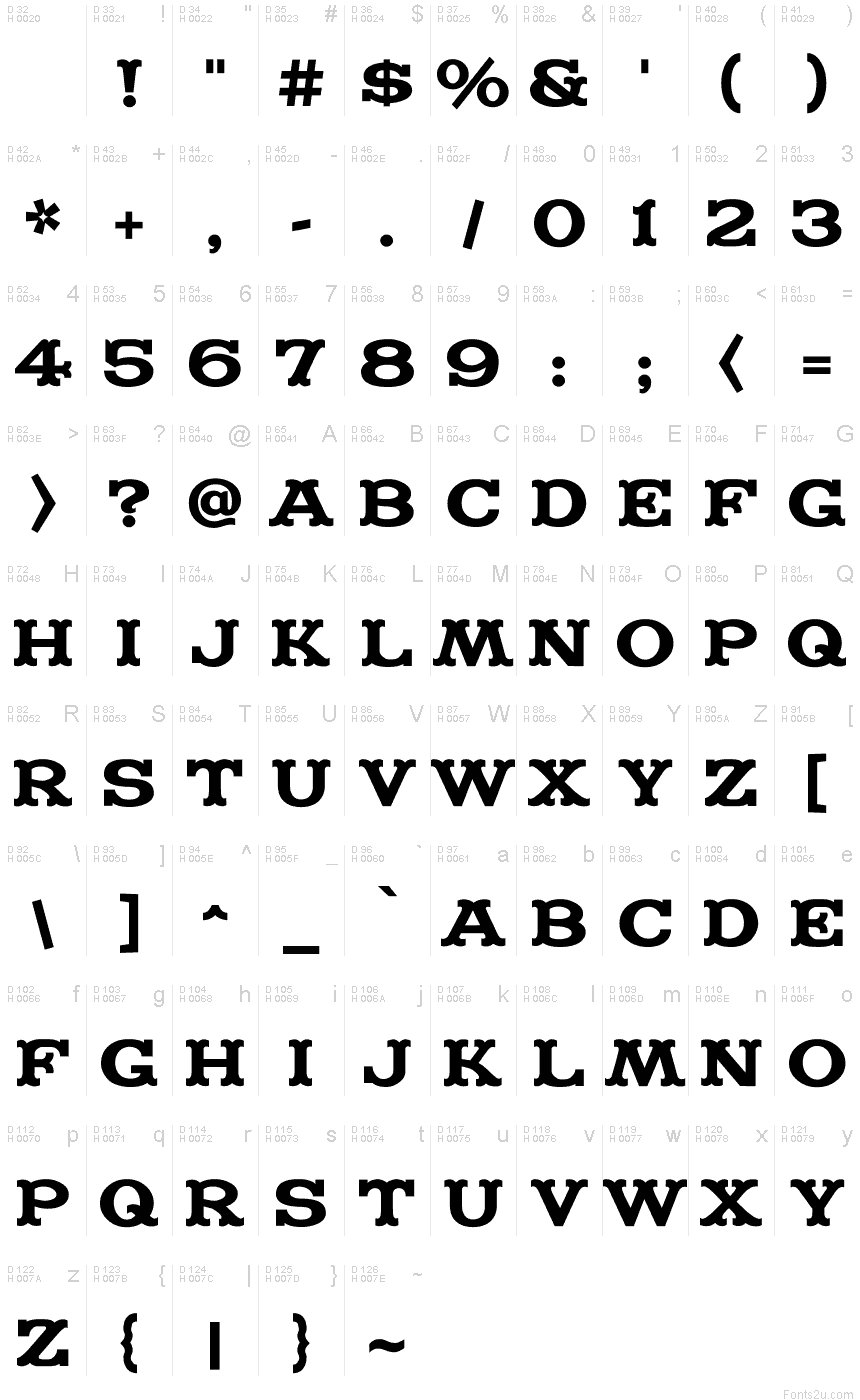
Madfont autorstwa Harolda Lohnera to bezpłatny krój pisma typu display, inspirowany magazynem MAD. Przekształca on napuchnięte szeryfy i głębokie, zaokrąglone łączenia starego logo w głośną, ciężką u góry sylwetkę. Szerokie krzywizny i tępe cięcia sprawiają, że litery wydają się jednocześnie zbite i elastyczne – bardziej jak tytuł komiksu niż typowy zachodni krój wyświetlaniowy.
Ta przesadzona masa nadaje krótkim nagłówkom wyrazistości na okładkach komiksów, plakatach parodystycznych, tytułach fanzinów, koszulkach czy ulotkach. Sprawdza się również w logotypach, nagłówkach sekcji i dużych cytatach, gdzie ta stłoczona sylwetka potrafi bez zbędnych efektów oddać psotny charakter w stylu magazynowym.